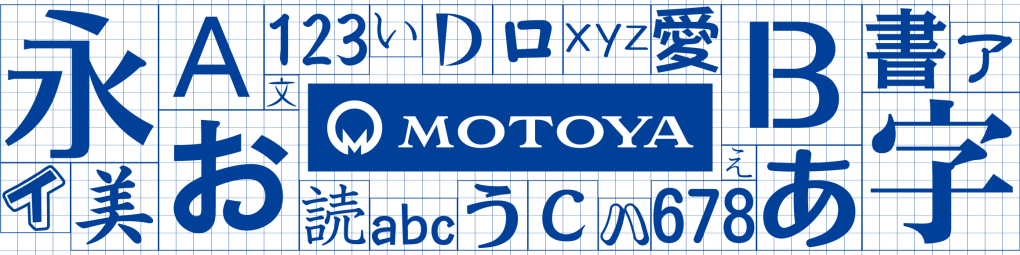
모토야, 뛰어난 가독성으로 전문적인 내용에 신뢰를 더하다
따끈따끈한 소식! 9월부터 산돌구름에서 만나볼 수 있는 일본어 폰트 브랜드사, 바로 ‘모토야‘입니다. 모토야는 무려 100년 역사를 지니고 있는 유서 깊은 일본 폰트 브랜드사예요. (산돌구름에서의 일본어 선택지가 또 한 번 넓혀졌죠?😎) 모토야 입점을 기념해 모토야와 나눈 일문일답을 만나보세요!
반갑습니다. 모토야, 어떤 기업인가요? 간단한 소개 부탁드려요!
모토야는 1922년 활자 제조 판매로 창업했습니다. 활자는 ‘인쇄의 원(元)이 된다’라는 의미에서 창업지인 간사이 지방의 사투리로 ‘원’을 ‘모토야’라고 발음하기 때문에 사명을 ‘모토야’라고 명명했죠. 모토야의 이념은 ‘읽기 쉬운 다양한 일본어 폰트 제공을 통해, 인쇄업계뿐만 아니라 모든 산업의 발전에 기여하는 것”입니다.
무려 100년의 역사라니 대단한데요, 모토야 폰트만의 매력이 있을까요?
모토야 폰트는 ‘뛰어난 가독성’과 ‘글자의 아름다움’이 가장 큰 특징이라고 할 수 있어요. 특히 본문용 서체는 일본의 대표 일간지 닛케이 신문, 산케이 신문뿐 아니라 다양한 서적, 사전 등에 사용되고 있어요. 한마디로 인쇄 업계에서 절대적인 지지를 받고 있다고 할 수 있겠네요!🙌 또한, 최근에는 디지털 환경에서의 폰트 이용 형태에 맞춰 가독성과 시인성을 고려한 현대식 폰트들이 지도 사이트, 차량용 기기, 의료 및 정밀 기기 등 새로운 분야에 널리 사용되고 있습니다..
닛케이 신문, 산케이 신문 적용 – 「MotoyaNewsM」
‘모토야 하면 ○○폰트’!라고 자신있게 소개할 수 있는 폰트가 있다면요?
모든 폰트가 자신 있지만, 3가지 패밀리를 소개해 드리겠습니다.
① 『MotoyaMincho』 : 글자가 많이 나열되어 있어도 가독성과 시인성이 높고, 깔끔한 느낌의 폰트입니다. ② 『SMotoyaSinkai』 : 전체적으로 부드러움과 강인함을 동시에 표현했습니다. 폰트에서 전문 서예가만의 풍격이 느껴지죠. ③ 『MotoyaAporo』 : 청량하고 모던한 폰트 이미지를 강조했고, 특히 디지털 폰트로 리뉴얼되어 사랑받고 있는 인기 폰트입니다.